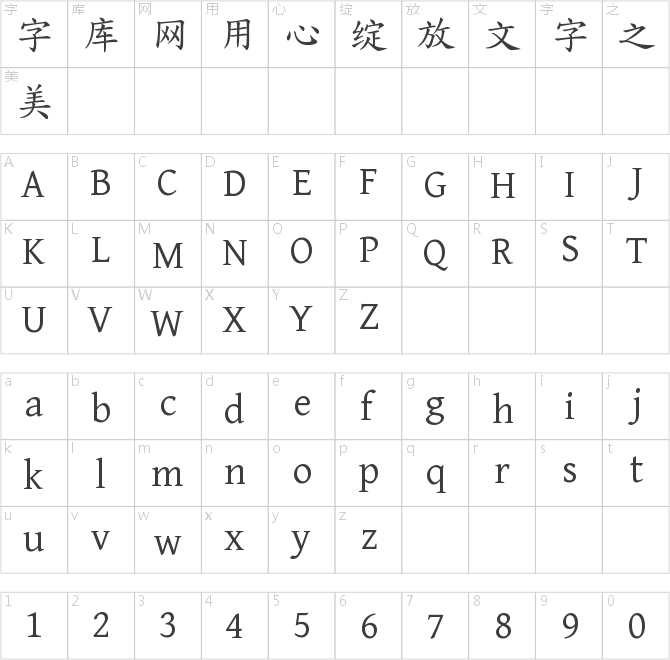
楷體
寒蟬正楷體由中文字體《全字庫正楷體》和西文字體《Gentium》重新整合優(yōu)化。全字庫正楷體字符非常豐富,還有多語言的支持,成為楷體的優(yōu)秀范本。但西文部分和中文部分不是特別融合。豎排比橫排文字排版更好,個人使用感受。西文字體Gentium是個人最喜歡的西文字體之一,是我認(rèn)為和楷體搭配最好的西文字體。無論是與文鼎U楷或者其他楷體,整體比原字體西文更加和諧統(tǒng)一。寒蟬正楷體字體字庫是一款讓人賞心悅目、百看不厭的中文字體,適合各類廣告和產(chǎn)品包裝設(shè)計(jì)應(yīng)用,字體大小33.4MB,格式為ttf字體,上傳用戶是sunlight,作者/版權(quán)方為寒蟬